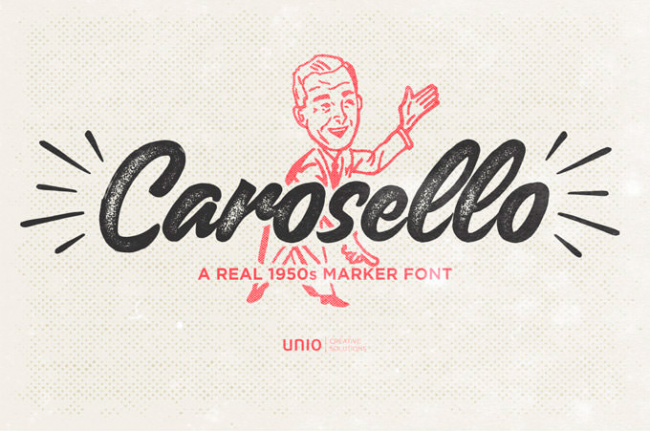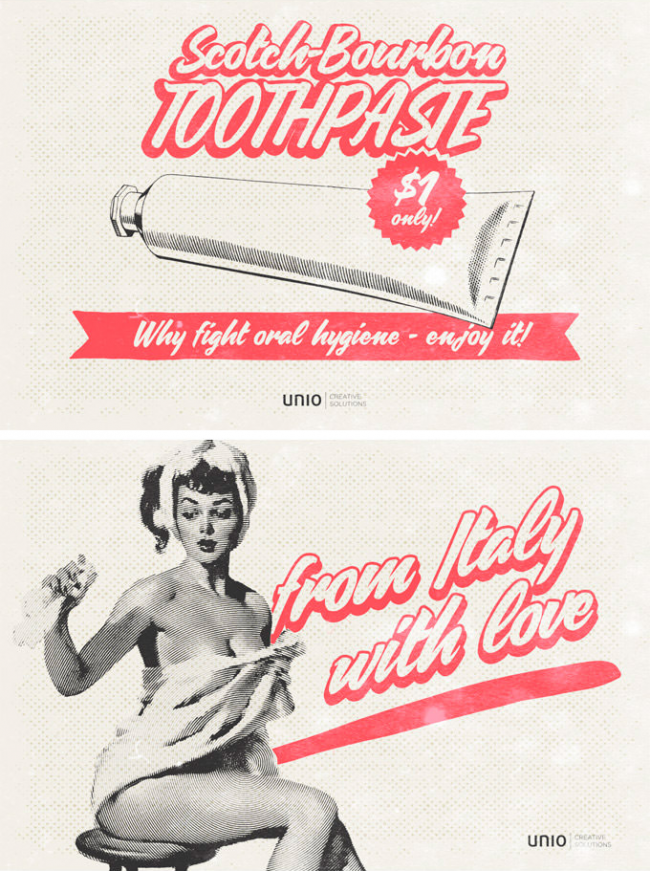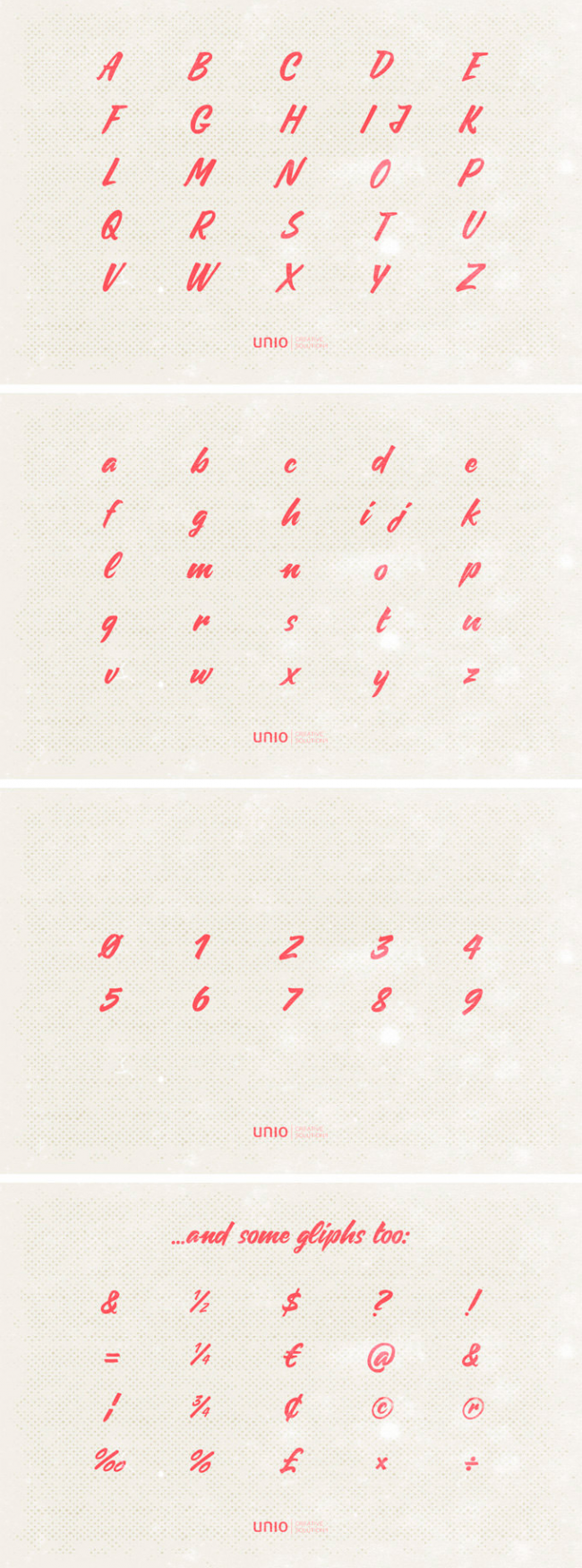
ヴィンテージな雰囲気が出る太めの英字フォント Carosello Font
Carosello Fontはヴィンテージな雰囲気が出る太めの英字フォントです。
少しコミカルで、力強さのあるフォントです。注目を引きたいバナーのデザインなどに使うと面白そうです。文字間はしっかり詰めて使いましょう。
↓ヴィンテージな雰囲気の広告デザインに合います。
↓大文字、小文字、数字に加えて、記号も揃っています。